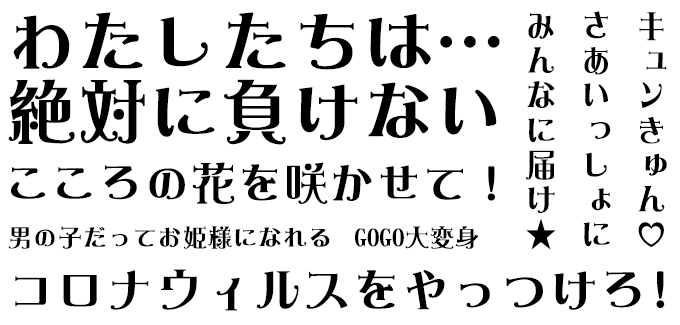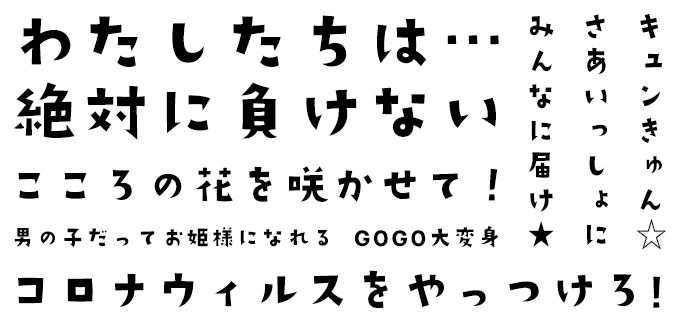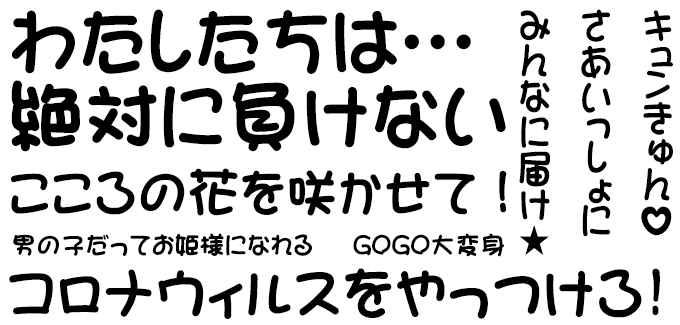
女児向けアニメに合うフォント 特化型 目的別フォントガイド
女児向けアニメに合うフォント:特化型 目的別フォントガイド #014
今回は女児向けアニメに合うフォント。日々フォントのことばかり考えている当店スタッフが直感的に選んだフォントをご紹介します。
女児向けアニメに合うフォントをスタッフが選びました
女児向けアニメに合うフォント #1 DFロマン雪A
DFロマン雪A【ダイナフォント】
大正時代の図案集に登場する婦人の華麗な装いや愛らしいスタイルをヒントにして古典ロマンの雰囲気を再現した書体。現代の女児向けアニメにもぴったりとはまります。
女児向けアニメに合うフォント #2 DSマンボ
DSマンボ【デザインシグナル】
太目の丸ゴシックベースのデザインで、やさしさと楽しさをもった動きのある書体。女の子向けのなかでも日常系の作品にぴったりと合います。
女児向けアニメに合うフォント #3 かりぐらスキップ
かりぐらスキップ【アトリエこたつ】
女児がおねえさんを気取っているようなフォントです。可愛らしくもスッキリとした印象です。
女児向けアニメに合うフォント #4 まーと太丸ゴシックネオ
まーと太丸ゴシックネオ【CFONT】
丸ゴシックの柔らかさを残しながら、スクエアなフォルムにデザイン。まじめすぎない、ふざけすぎない、そんな女児向けアニメに最適です。
女児向けアニメに合うフォント #5 恋みんちょう
恋みんちょう【かに沢のりお】
女児アニメ・女児ゲームで映える、ハートを散りばめたかわいい手作りの明朝体フォントです。縦書き・漢字にも対応しています。
女児向けアニメに合うフォント #6 DF優雅宋 W7
DF優雅宋 W7【ダイナフォント】
ストロークの先端と末端に欧文書体の花文字のような装飾が施されているのが特徴的な書体。この特徴が古典的な洋風感を引き出し、女児向けアニメにぴったりな優雅さや華やかさを表現しています。
女児向けアニメに合うフォント #7 VDL メガ丸 Ultra
VDL メガ丸 Ultra【視覚デザイン研究所】
絶妙のアンバランス感と強い個性を持ち可読性も考慮。軽やかなリズムが女の子らしさを表現するのに最適です。また「きゅん」でも「キュン」でも最高の仕上がりを見せます。
女児向けアニメに合うフォント #8 DF麗雅宋
DF麗雅宋【ダイナフォント】
明朝体のストロークをより美しく、そして特徴的にアレンジし、女児向けアニメにぴったりな華麗な雰囲気を演出したロマン風書体です。
女児向けアニメに合うフォント #9 DSきりぎりす
DSきりぎりす【デザインシグナル】
切り絵のような、切り文字のようなイメージで、自由に枠にとらわれない手書き風の文字。タテでもヨコでもゆったりとした印象で名越されたアナログ感は優しい女の子のイメージにもぴったりと合います。
女児向けアニメに合うフォント #10 DFPパンダ体 W9
DFPパンダ体 W9【ダイナフォント】
オーソドックスな丸ゴシックの漢字に、色々な角度のパンダが貼り付いてます。思わずウフフとなる可愛さです。
女児向けアニメに合うフォント #11 ましゅまろポップ ハート
ましゅまろポップ ハート 【かに沢のりお】
女児が大好きなハートが散りばめられています。マシュマロのようなぽってり丸めのデザインで見やすさも二重丸◎。
女児向けアニメに合うフォント #12 AR POP5H
AR POP5H【アーフィック】
まる文字っぽくてクセがあって可愛いのに可読性も高く読み文字として使うこともできる万能なフォント。
女児向けアニメに合うフォント #13 DSかざぐるま
DSかざぐるま【デザインシグナル】